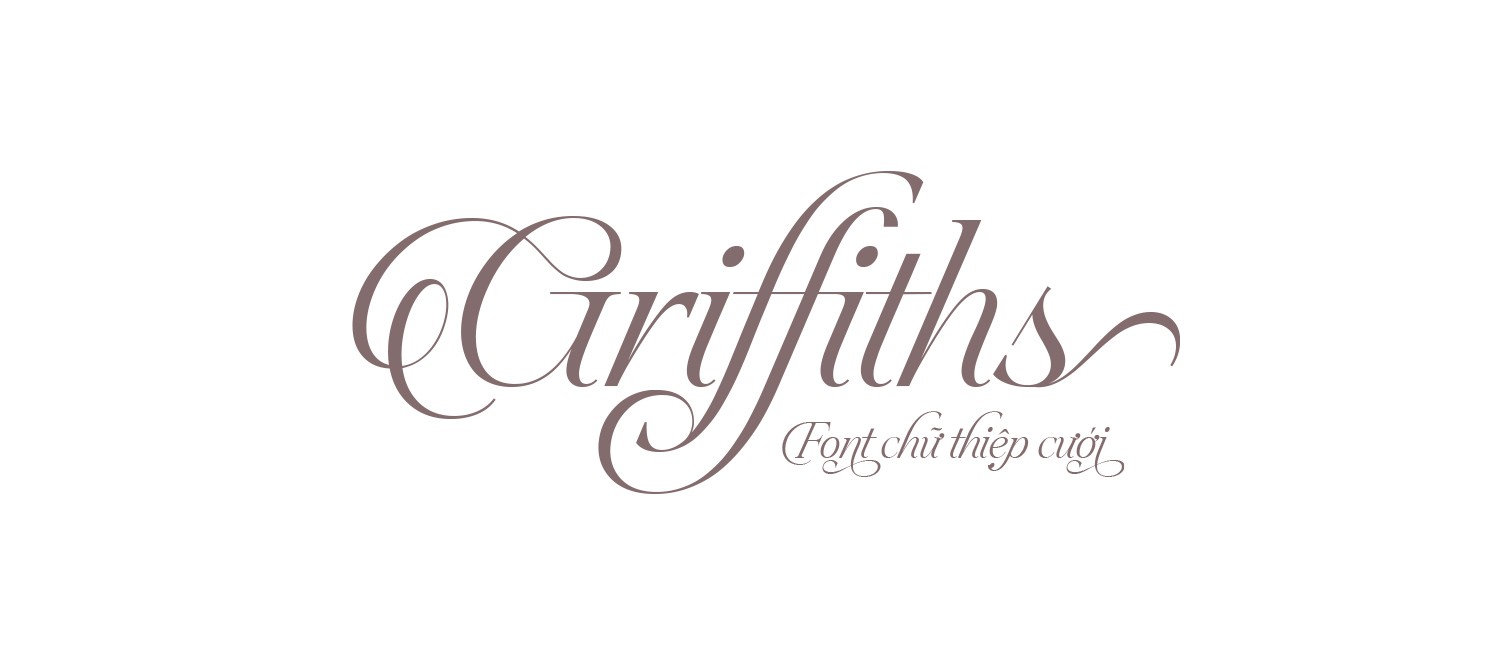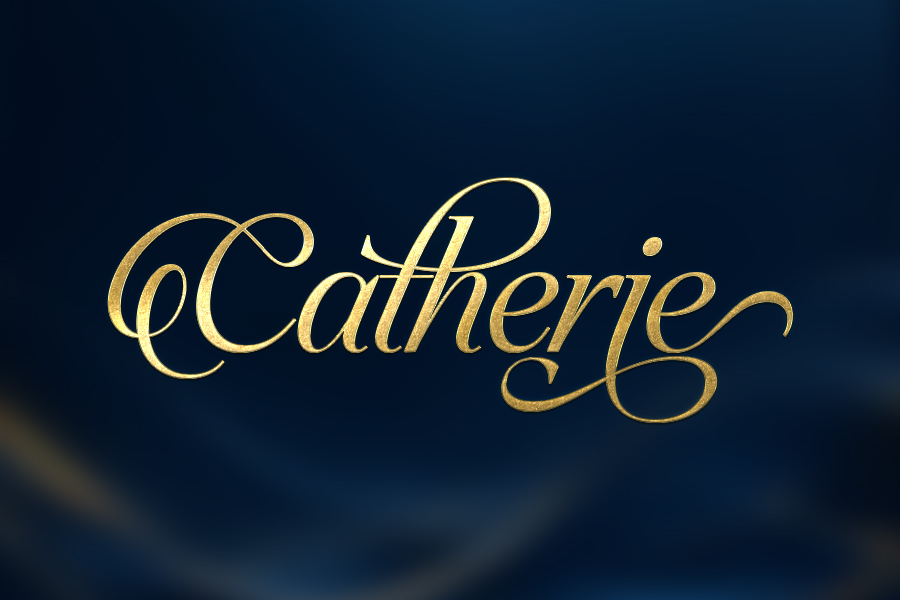
Font chữ TH Griffiths quả là một lựa chọn hoàn hảo để tạo nên những thiết kế thiệp cưới sang trọng và tinh tế. Với những đường nét tinh xảo, TH Griffiths Regular không chỉ mang lại cảm giác trang nhã mà còn rất dễ đọc, làm cho nó trở thành lựa chọn lý tưởng cho nhiều dự án thiết kế thiệp cưới khác nhau. Font chữ thiệp cưới TH Griffiths sẽ giúp cho những lời mời của bạn trở nên thật đặc biệt và đáng nhớ.
Nét chữ thanh lịch, mềm mại: Các nét chữ của TH Griffiths Regular được thiết kế với độ cong nhẹ nhàng, tạo cảm giác uyển chuyển và thanh thoát. Điều này mang đến sự tinh tế và sang trọng cho thiết kế.
Phong cách cổ điển: Font chữ này mang đậm dấu ấn của phong cách cổ điển, gợi nhớ đến những tấm thiệp cưới truyền thống với nét đẹp lãng mạn. Nét chữ của font chữ thiệp cưới TH Griffiths Regular hài hòa không quá dày nhưng vẫn dễ đọc đủ để làm nổi bật các thông tin và tạo ấn sâu sắc. Phong cách này phù hợp với những tấm thiệp cưới sang trọng quý phái, cũng như các ấn phẩm in cao cấp, bằng khen vinh danh…
Dễ đọc: Mặc dù mang đậm phong cách cổ điển nhưng Griffiths Regular vẫn đảm bảo tính dễ đọc, giúp thông tin trên thiệp cưới được truyền đạt rõ ràng. Nhờ vào sự hài hòa hoàn hảo trong nét chữ lên dù viết chữ dài thì người đọc vẫn không bị mỏi mắt. Điều này làm cho nó trở nên lý tưởng cho các ấn phẩm như sách, báo, hoặc các tài liệu học thuật, nơi mà tính dễ đọc được đặt lên hàng đầu.
Linh hoạt: Font chữ này có thể kết hợp hài hòa với nhiều phong cách thiết kế khác nhau, từ cổ điển đến hiện đại, từ đơn giản đến cầu kỳ. Font chữ có thể dùng trong nhiều mục đích khác nhau ngoài thiệp cưới. Điều này rất cần thiết khi lựa chọn font chữ thiết kế.
Phù hợp với nhiều loại giấy: Griffiths Regular trông rất đẹp khi được in trên các loại giấy cao cấp như giấy mỹ thuật, giấy kraft hoặc giấy có vân. Font chữ luôn nổi bật khi in với bất kỳ loại giấy nào.
Tiêu đề: Font chữ Griffiths Regular thường được sử dụng để tạo điểm nhấn cho tiêu đề của thiệp cưới, giúp thu hút sự chú ý của người xem.
Nội dung: Với nét chữ hài hòa dễ đọc, font chữ này cũng rất phù hợp để in nội dung chi tiết của thiệp cưới như tên cô dâu chú rể, ngày giờ, địa điểm tổ chức.
Lời mời: Viết lời mời bằng font chữ Griffiths Regular sẽ tạo cảm giác chân thành và ấm áp. Giúp người viết gửi tất cả tình cảm yêu thương vào lời mời sang trọng.
Trang trí: Font chữ này có thể được sử dụng để tạo các họa tiết trang trí nhỏ như tên viết tắt của cô dâu chú rể, ngày kỷ niệm…
Kết hợp với màu sắc: Font chữ Griffiths Regular sẽ trở nên nổi bật hơn khi kết hợp với các màu sắc pastel nhẹ nhàng như hồng nhạt, xanh nhạt, vàng kem... hoặc các màu sắc đậm như xanh navy, đỏ burgundy để tạo điểm nhấn.
Sử dụng giấy chất lượng cao: Để tôn lên vẻ đẹp của font chữ Griffiths Regular, bạn nên chọn loại giấy có chất lượng cao, bề mặt mịn màng. Sẽ giúp tấm thiệp cưới của bạn trở lên sang trọng hơn.
Trang trí thêm: Bạn có thể trang trí thêm cho thiệp cưới bằng các họa tiết hoa văn, lá cây,hoặc các yếu tố trang trí khác để tạo nên một thiết kế hoàn chỉnh.
Kết Luận
Font chữ Griffiths Regular là sự kết hợp hoàn hảo giữa vẻ đẹp cổ điển và tính đa dụng trong thiết kế. Với những đặc điểm nổi bật và sự linh hoạt, Griffiths Regular sẽ giúp bạn tạo ra những thiết kế độc đáo và mang đậm dấu ấn cá nhân như thiệp cưới, logo... Nếu bạn đang tìm kiếm một font chữ thiệp cưới để nâng cao giá trị thẩm mỹ cho thiết kế của mình, Griffiths Regular chắc chắn sẽ không làm bạn thất vọng. Hãy thử nghiệm và trải nghiệm sự khác biệt mà Griffiths Regular có thể mang lại cho dự án của bạn.